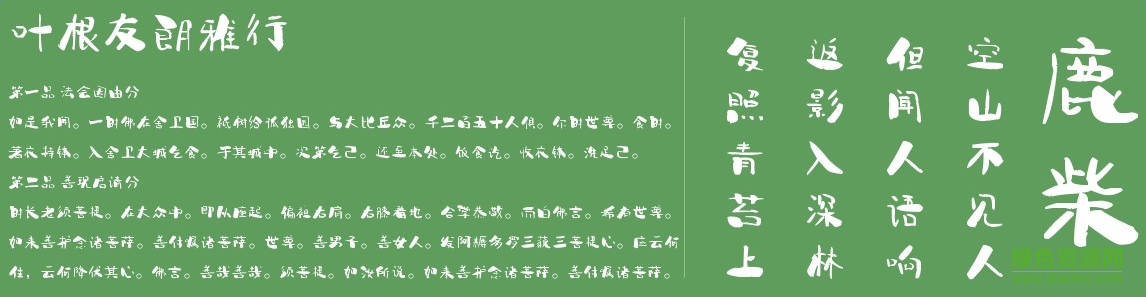
葉根友朗雅行字體是一款由知名書法家葉根友創(chuàng)造的字體,適用于藝術(shù)設(shè)計(jì)、海報(bào)設(shè)計(jì)、字體排版等方面,有需要的朋友們不要錯(cuò)過了。小編為大家提供免費(fèi)下載地址。歡迎大家來綠色資源網(wǎng)踴躍下載哦!
葉根友朗雅行字體,該字體為2016年發(fā)行的第一款書法字體,整個(gè)字體靈動(dòng)、活潑,創(chuàng)意新穎,是標(biāo)題用字以及海報(bào)設(shè)計(jì)等用字不錯(cuò)的選擇。
葉根友朗雅行字體,用途廣泛,是葉根友先生的手寫字體,字體非常靈巧、有創(chuàng)意,藝術(shù)設(shè)計(jì)、廣告設(shè)計(jì)可以使用到。各位字體收藏者可以來看看。